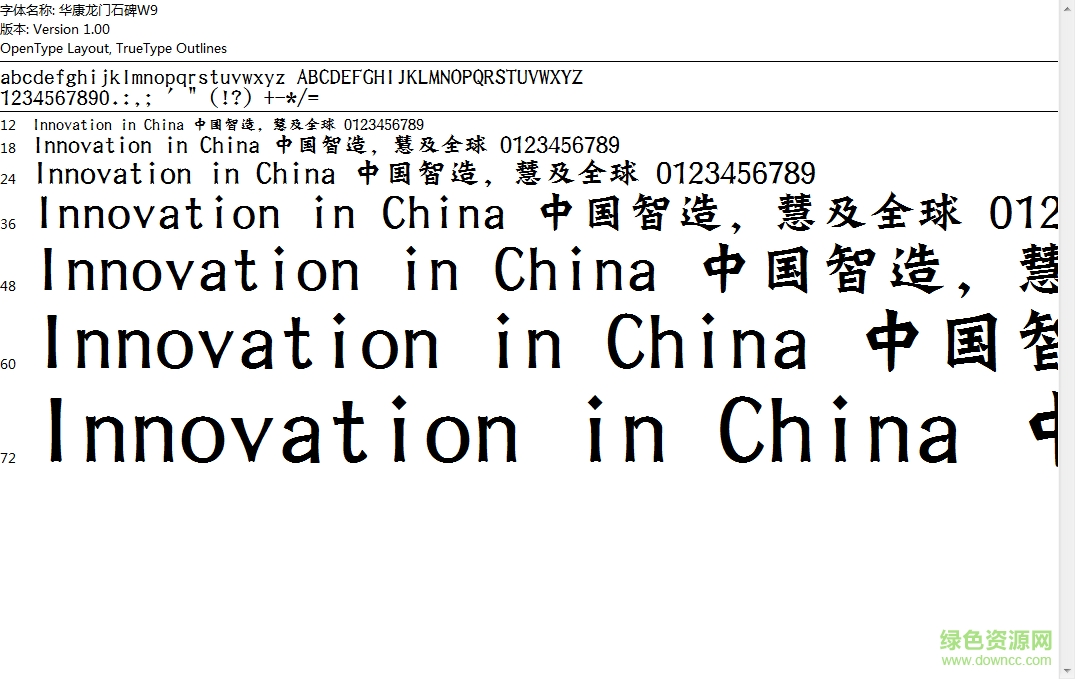
dfplongmenw9字體是華康龍門石碑W9的英文縮寫名稱,該字體典雅大方,常用于雜志、書籍、影視字幕、報(bào)紙排版等領(lǐng)域,需要的朋友快來綠色資源網(wǎng)下載吧!
dfplongmenw9是一款用于藝術(shù)設(shè)計(jì)方面的字體,廣告、平面、雜志、排版等都可以用得到這款字體,由綠色資源網(wǎng)素材提供免費(fèi)下載